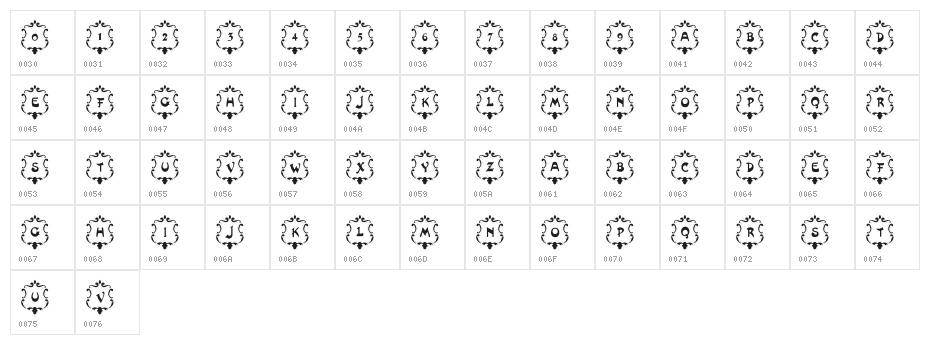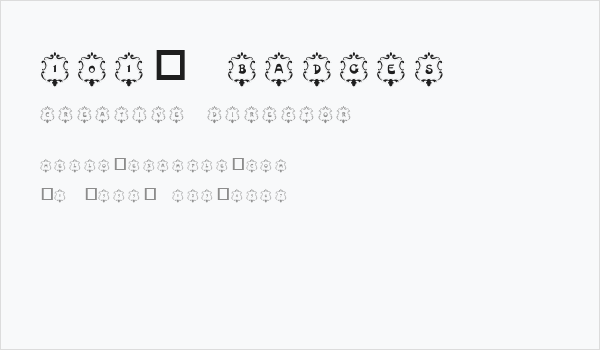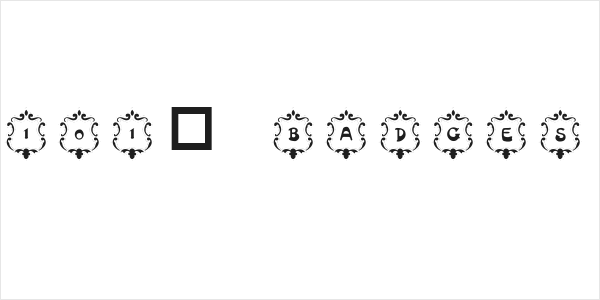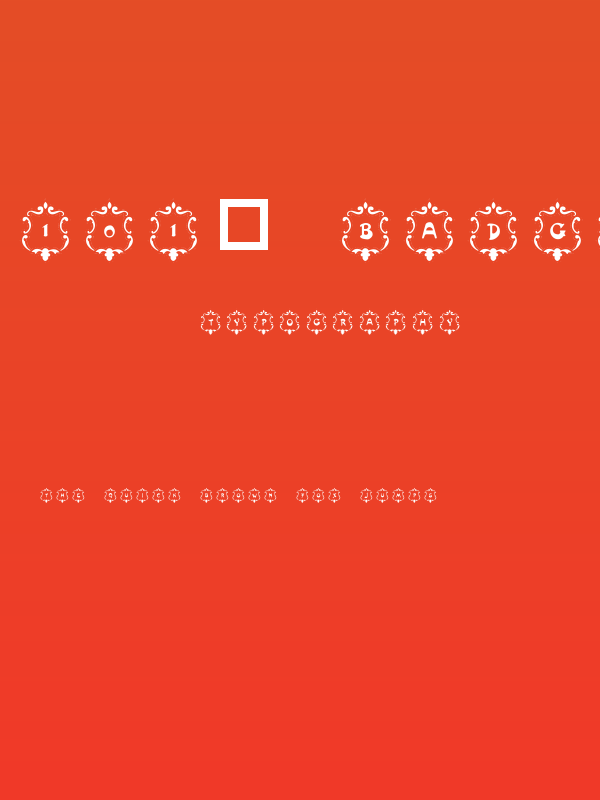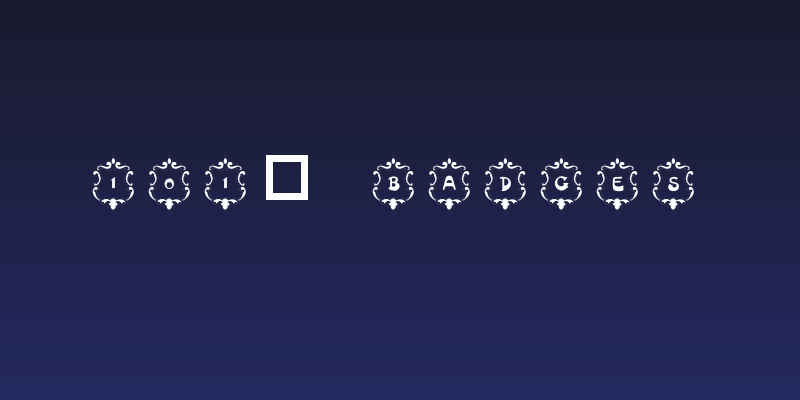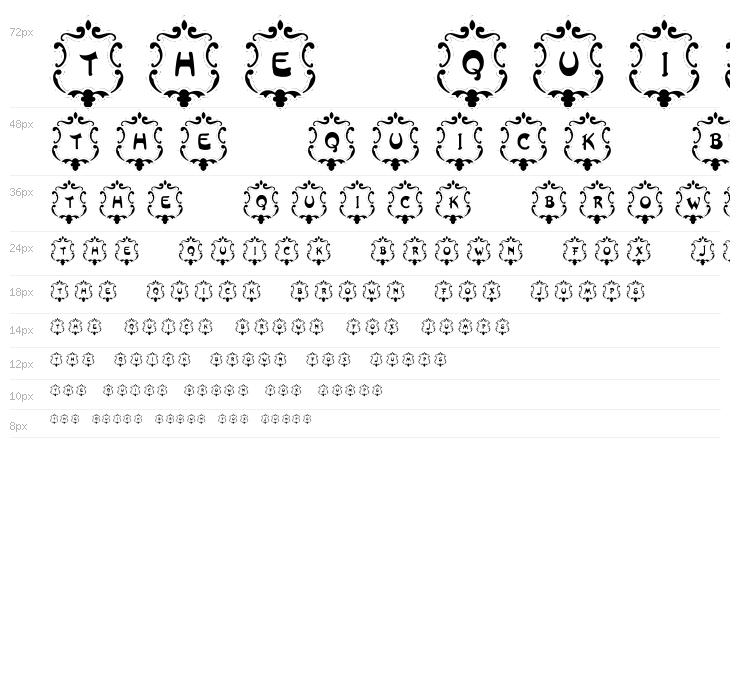
101! Badges Font
| 整体风格 | Vintage, Decorative |
| 使用场景 | Logos, Invitations, Certificates |
| 推荐项目 | Ideal for wedding invitations, certificates, branding for luxury products, or any project needing a touch of elegance and formality. |